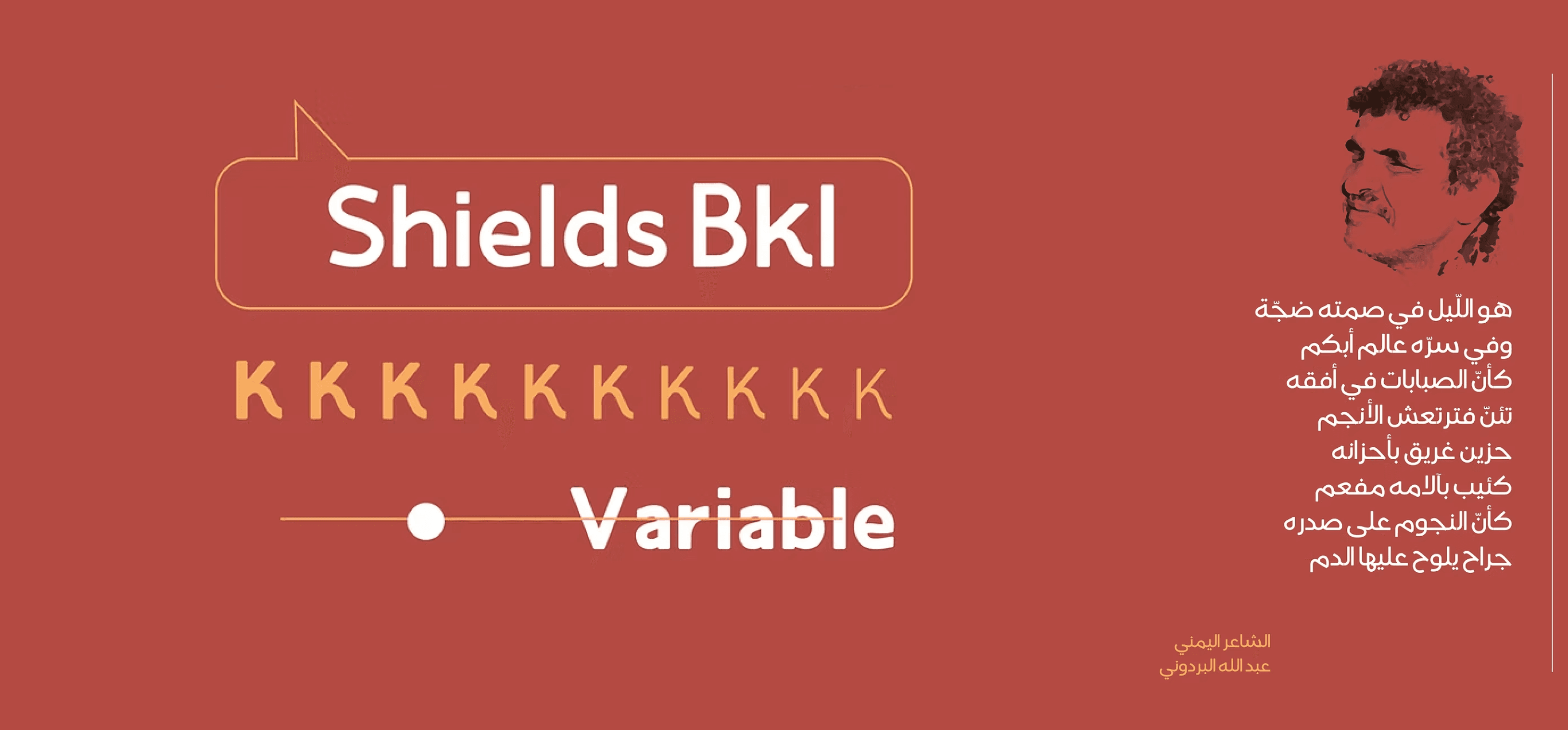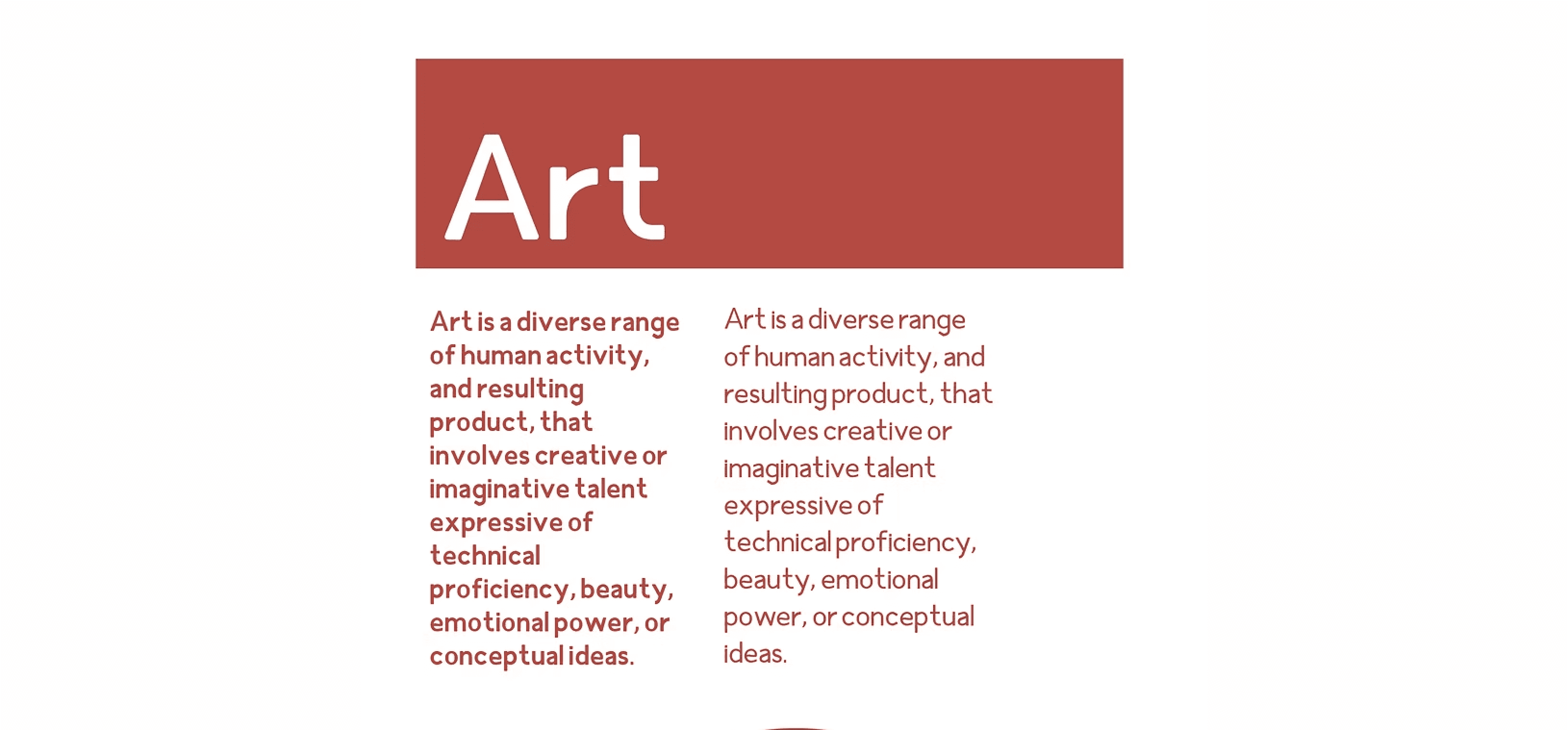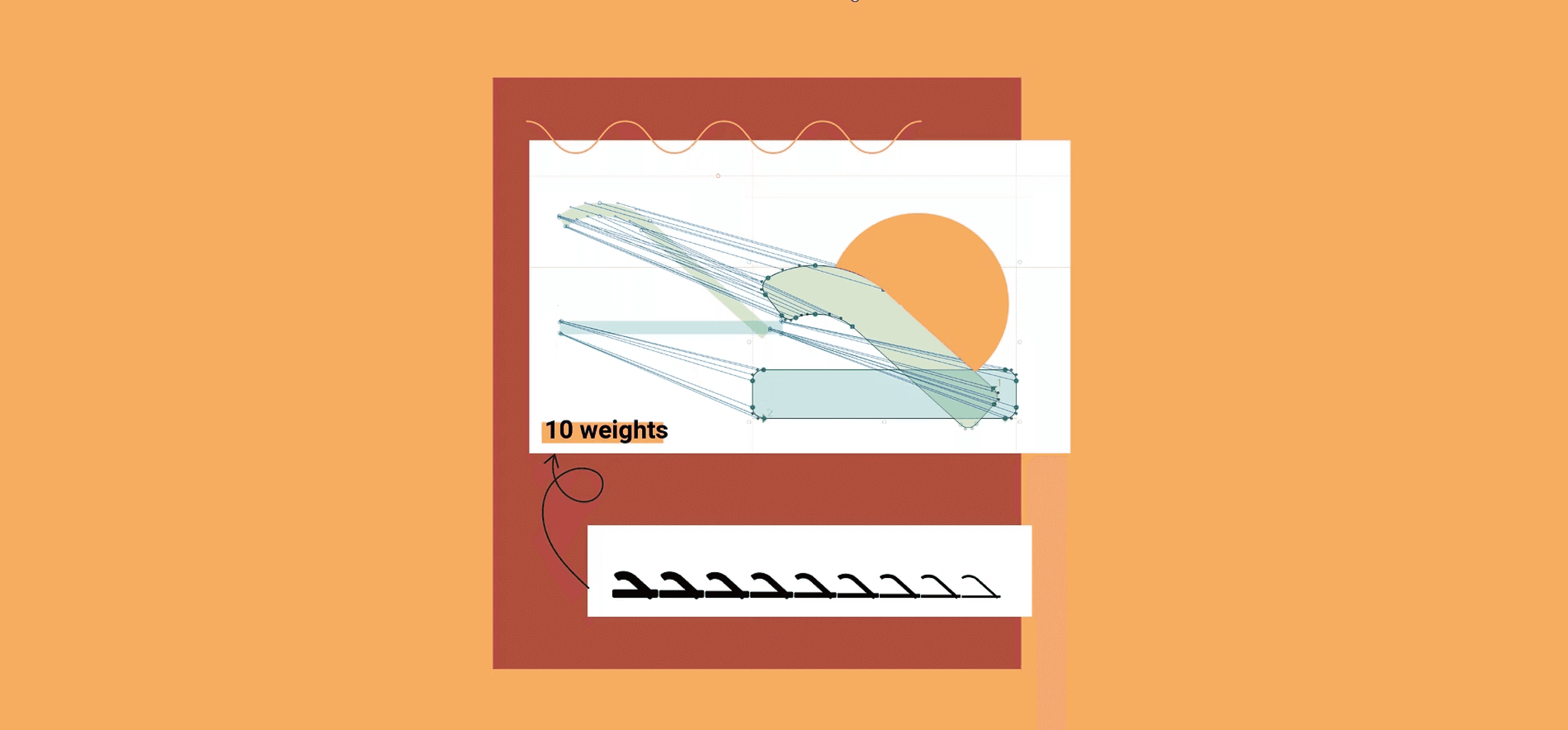
خط Shields-Regular مثالي لأي مصمم مبدع يبحث عن تجربة جديدة ومختلفة. يتميز هذا الخط بلمسة عصرية جريئة تجعله يلفت الانتباه ويبرز في أي تصميم.
يحتوي على مجموعة واسعة من الحروف والرموز التي تتيح لك إنشاء أعمال طباعية فريدة تُميز تصميمك عن الآخرين.
تتضمن الحزمة أيضًا عدة أنماط مختلفة، مما يمنحك مرونة أكبر لاختيار الأسلوب المثالي لأي مشروع.